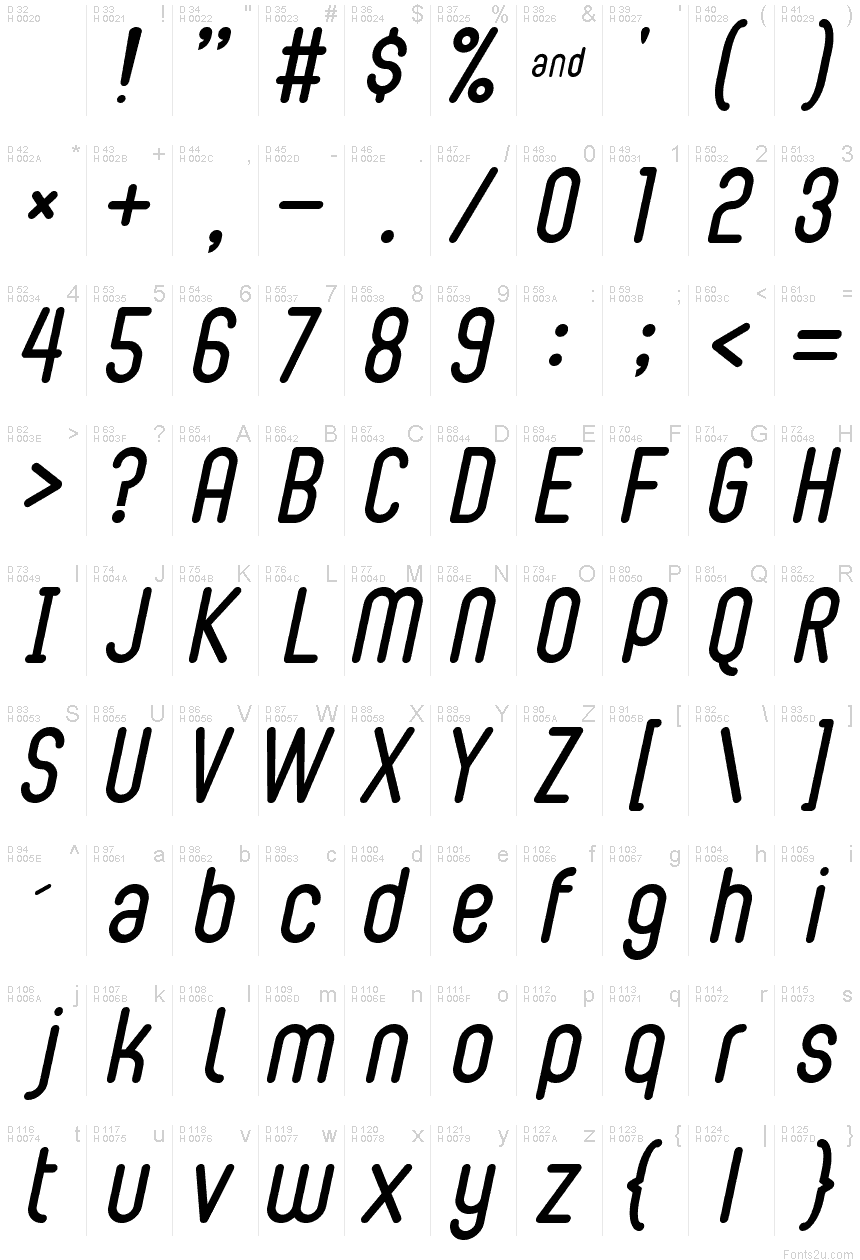
خط BubbleBoy2 من تصميم Jakob Fischer هو خط عرض (Display) مجاني وعصري، يتميز بطاقة ناعمة ومرنة مع ميل ديناميكي إلى الأمام. تمنحك ضرباته المستديرة وأشكاله المكثفة إحساسًا بحروف "الفقاعات" المرسومة يدويًا، ولكن مع معالجة دقيقة تضمن الحفاظ على طابع مرح دون التضحية بوضوح القراءة. إيقاع الخط حيوي ومضبوط، مما يضفي على العناوين مظهرًا نشيطًا مليئًا بالحركة يسهل قراءته في لمح البصر.
باستخدام BubbleBoy2، ستبرز عناوينك وشعاراتك بشكل رائع على منتجات الأطفال، وأغلفة القصص المصورة، وعبوات الوجبات الخفيفة، ومنشورات الفعاليات، والملصقات، والمنشورات الجريئة على وسائل التواصل الاجتماعي. يتألق هذا الخط المجاني عند استخدامه بأحجام كبيرة حيث تبرز انحناءاته، لذا ننصح بدمجه مع خط هندسي بسيط (Sans Serif) للنصوص الفرعية، لضمان عدم منافسته لشخصية BubbleBoy2 المرحة.